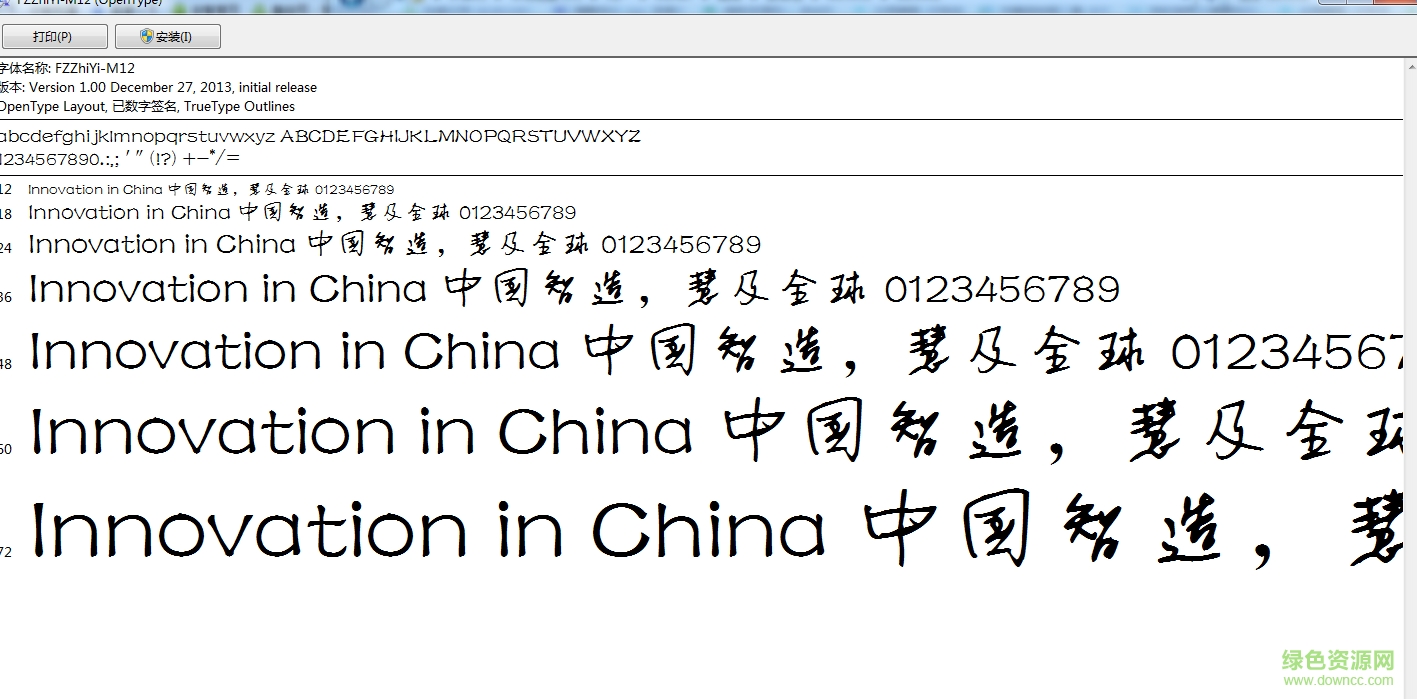
硬筆情書體是一款用于書寫設(shè)計(jì)方面的字體,硬筆風(fēng)格,該字體風(fēng)度超逸、墨采飛動(dòng),靈秀清麗,富含韻味,應(yīng)用領(lǐng)域極廣!需要的朋友趕緊來綠色資源網(wǎng)下載喲!
硬筆情書體是線條非常細(xì)膩的中文簡體漢字,該字體纖細(xì)大方,結(jié)構(gòu)清晰,整體風(fēng)格非常出色,能夠適用于廣告設(shè)計(jì)、名片設(shè)計(jì)、包裝印刷、產(chǎn)品設(shè)計(jì)等應(yīng)用